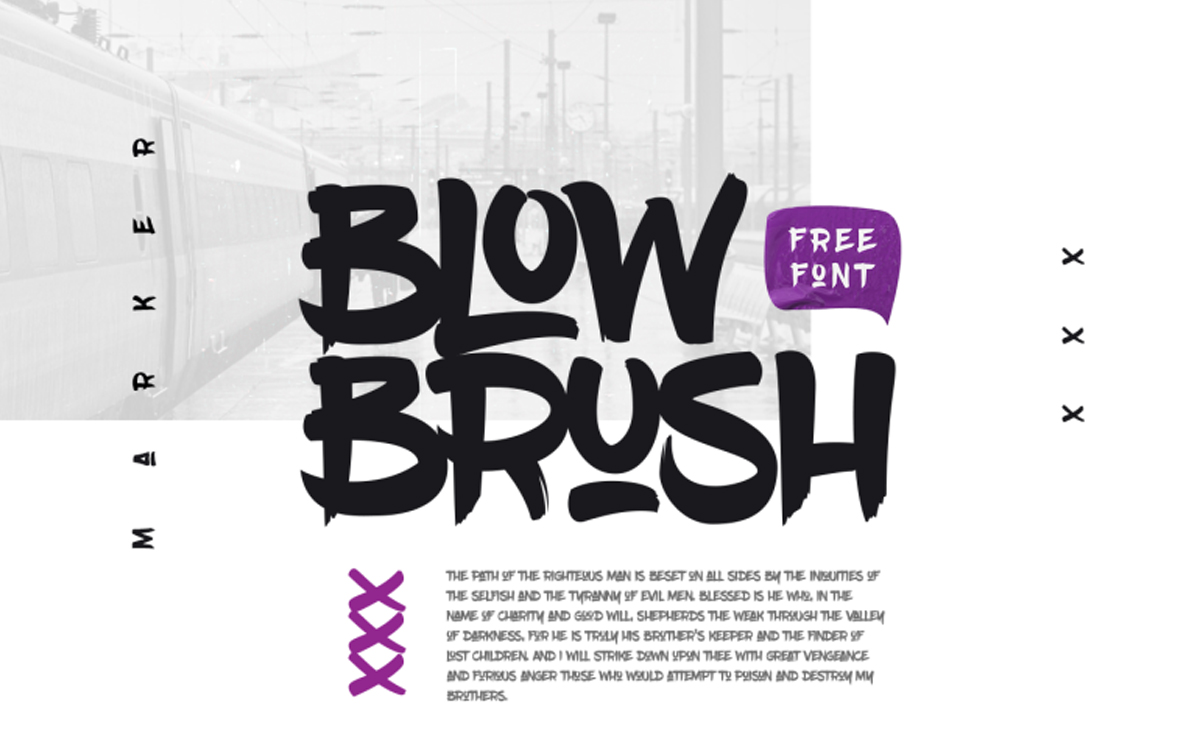
Font chữ brush SVN BlowBrush Việt hóa
<p>Nếu bạn đang tìm kiếm một phông chữ thể hiện sự tự do, phá cách và mang đậm tinh thần nghệ thuật đường phố, font chữ brush SVN BlowBrush Việt hóa chính là sự lựa chọn tuyệt vời không thể bỏ qua. Phông chữ này sở hữu các nét cọ thô ráp nhưng cực kỳ tự nhiên, kết hợp hoàn hảo với bộ dấu tiếng Việt chuẩn chỉnh giúp tôn vinh trọn vẹn thông điệp thiết kế của bạn. Dù là poster, áo thun hay banner truyền thông, SVN BlowBrush sẽ ngay lập tức biến tác phẩm của bạn trở nên nổi bật và thu hút mọi ánh nhìn.</p>
Font Chữ Brush SVN BlowBrush Việt Hóa – Phong Cách Graffiti Đường Phố Phá Cách Cho Thiết Kế Hiện Đại
Trong nghệ thuật typography, phông chữ dạng cọ vẽ (brush font) luôn giữ một vị trí đặc biệt nhờ khả năng truyền tải cảm xúc mạnh mẽ, chân thật và không bị gò bó bởi những quy chuẩn hình học thông thường. Trong số đó, SVN BlowBrush nổi lên như một hình mẫu lý tưởng đại diện cho phong cách streetwear, graffiti và nghệ thuật vẽ tường đầy năng lượng. Phông chữ nguyên bản do tác giả Petar Acanski sáng tạo đã được đội ngũ SVN Việt hóa chỉn chu, mang đến một công cụ đắc lực cho cộng đồng thiết kế tại Việt Nam.
Điểm làm nên sức hút khác biệt của SVN BlowBrush chính là các nét chữ mô phỏng lại thao tác đưa bút marker hoặc cọ nét lớn một cách phóng khoáng. Khoảng trống ngẫu hứng cùng cấu trúc nét dày dặn giúp phông chữ vừa mang vẻ bụi phủi, vừa đảm bảo tính hiển thị rõ ràng trên đa dạng nền tảng. Khi được bổ sung trọn bộ ký tự tiếng Việt với các dấu thanh được tạo hình khéo léo, phông chữ giữ nguyên được thần thái cuốn hút ban đầu mà không hề bị gượng ép hay mất cân đối typography.
Các Chức Năng Và Đặc Điểm Nổi Bật Của Font SVN BlowBrush Việt Hóa
1. Đường Nét Brush Vẽ Tay Chân Thực Và Đầy Sức Sống
SVN BlowBrush tái hiện một cách sống động hiệu ứng mực bám trên bề mặt giấy nhám hoặc tường gạch thông qua các nét cọ nét đậm, nét rỗng đầy ngẫu hứng. Mỗi chữ cái được thiết kế như một tác phẩm viết tay tự do, mang lại cảm giác phóng khoáng, hiện đại và vô cùng chân thực. Tính năng này giúp loại bỏ sự khô cứng của các phông chữ kỹ thuật số thông thường, mang đến cho sản phẩm thiết kế của bạn chiều sâu nghệ thuật và cá tính không thể hòa lẫn.
2. Bộ Ký Tự Việt Hóa Chuẩn SVN Hoàn Hảo Và Tự Nhiên
Điểm nâng cấp quan trọng nhất của phiên bản SVN BlowBrush chính là sự hỗ trợ trọn vẹn cho bộ gõ tiếng Việt. Tất cả các ký tự có dấu như Ă, Â, Đ, Ê, Ô, Ơ, Ư cùng hệ thống 5 dấu thanh (huyền, sắc, hỏi, ngã, nặng) đều được tinh chỉnh tỉ mỉ. Các dấu thanh được đặt ở vị trí hợp lý, có độ nghiêng và nét cọ đồng bộ tuyệt đối với thân chữ chính, giúp văn bản tiếng Việt hiển thị đẹp mắt, tự nhiên mà không bị đè nét hay gây rối thị giác người xem.
3. Đầy Đủ Chữ Số, Dấu Câu Và Ký Tự Đặc Biệt Đồng Bộ
Không chỉ chú trọng vào các chữ cái cơ bản, bộ phông chữ SVN BlowBrush Việt hóa còn bao gồm trọn bộ các chữ số từ 0 đến 9, các dấu câu cơ bản cùng nhiều ký tự đặc biệt phong phú. Tất cả đều tuân thủ nghiêm ngặt phong cách bút vẽ nét cọ bụi phủi. Sự đồng bộ này giúp các designer thoải mái sáng tạo các con số ấn tượng cho chiến dịch giảm giá, thiết kế đồng hồ đếm ngược, biểu đồ nghệ thuật hay các trích dẫn (quotes) ngắn trên mạng xã hội.</p>
4. Tối Ưu Khả Năng Hiển Thị Trên Nhiều Ấn Phẩm Đa Dạng
Một trong những điểm yếu của nhiều font brush là khó đọc khi ứng dụng vào thực tế. Tuy nhiên, SVN BlowBrush được tối ưu hóa xuất sắc về khoảng cách giữa các chữ cái (kerning) và tỷ lệ khung chữ. Phông chữ này ứng dụng cực kỳ hiệu quả trong nhiều lĩnh vực như thiết kế áo thun thời trang streetwear, bìa album nhạc Rap/Hip-hop, poster phim hành động, banner E-Sports, logo sự kiện thể thao hay làm thumbnail cho các video YouTube triệu view.
5. Tương Thích Tuyệt Đối Với Mọi Phần Mềm Thiết Kế Và Dựng Video
Font SVN BlowBrush Việt hóa được đóng gói dưới dạng định dạng chuẩn Vector Font (OTF/TTF), giúp tương thích mượt mà trên cả hệ điều hành Windows và macOS. Bạn có thể dễ dàng sử dụng phông chữ này trên các công cụ đồ họa chuyên nghiệp như Adobe Photoshop, Adobe Illustrator, CorelDraw, Figma, Canva, cũng như các phần mềm dựng phim phổ biến như Adobe Premiere, CapCut, DaVinci Resolve hay thậm chí là các phần mềm văn phòng Microsoft Office.
Tại Sao Bạn Nên Sử Dụng Font SVN BlowBrush Trong Dự Án Thiết Kế?
Trong bối cảnh thị trường quảng cáo và truyền thông hình ảnh ngày càng cạnh tranh, việc thu hút sự chú ý của khách hàng ngay trong vài giây đầu tiên là vô cùng quan trọng. Các phông chữ sans-serif truyền thống tuy sạch sẽ nhưng đôi khi thiếu đi điểm nhấn cảm xúc. SVN BlowBrush xuất hiện như giải pháp cứu cánh giúp bạn tạo nên sự đột phá về mặt thị giác.
Sự kết hợp giữa nét vẽ tay tự do và cấu trúc chữ vững chắc của SVN BlowBrush đem lại cho tác phẩm cảm giác mạnh mẽ, trẻ trung và tràn đầy năng lượng tích cực. Phông chữ này đặc biệt phù hợp với các thương hiệu hướng tới đối tượng khách hàng trẻ, những người yêu thích sự độc đáo, phá cách và không ngần ngại thể hiện cái tôi cá nhân.